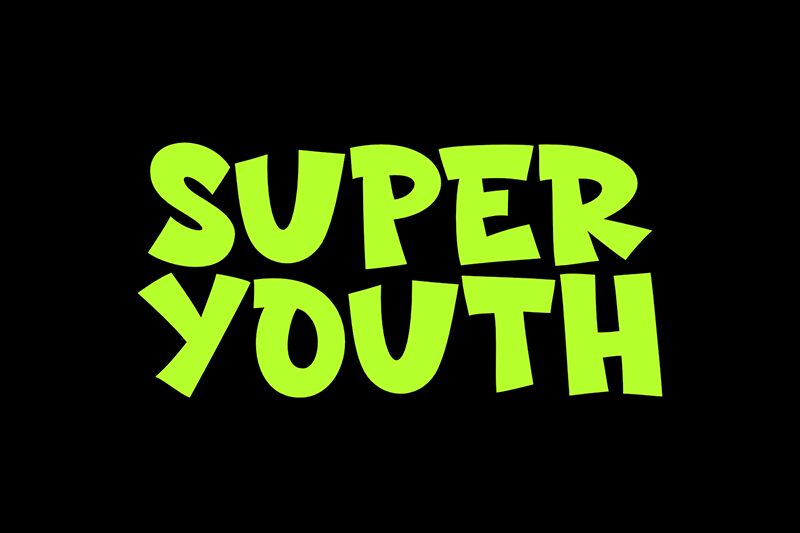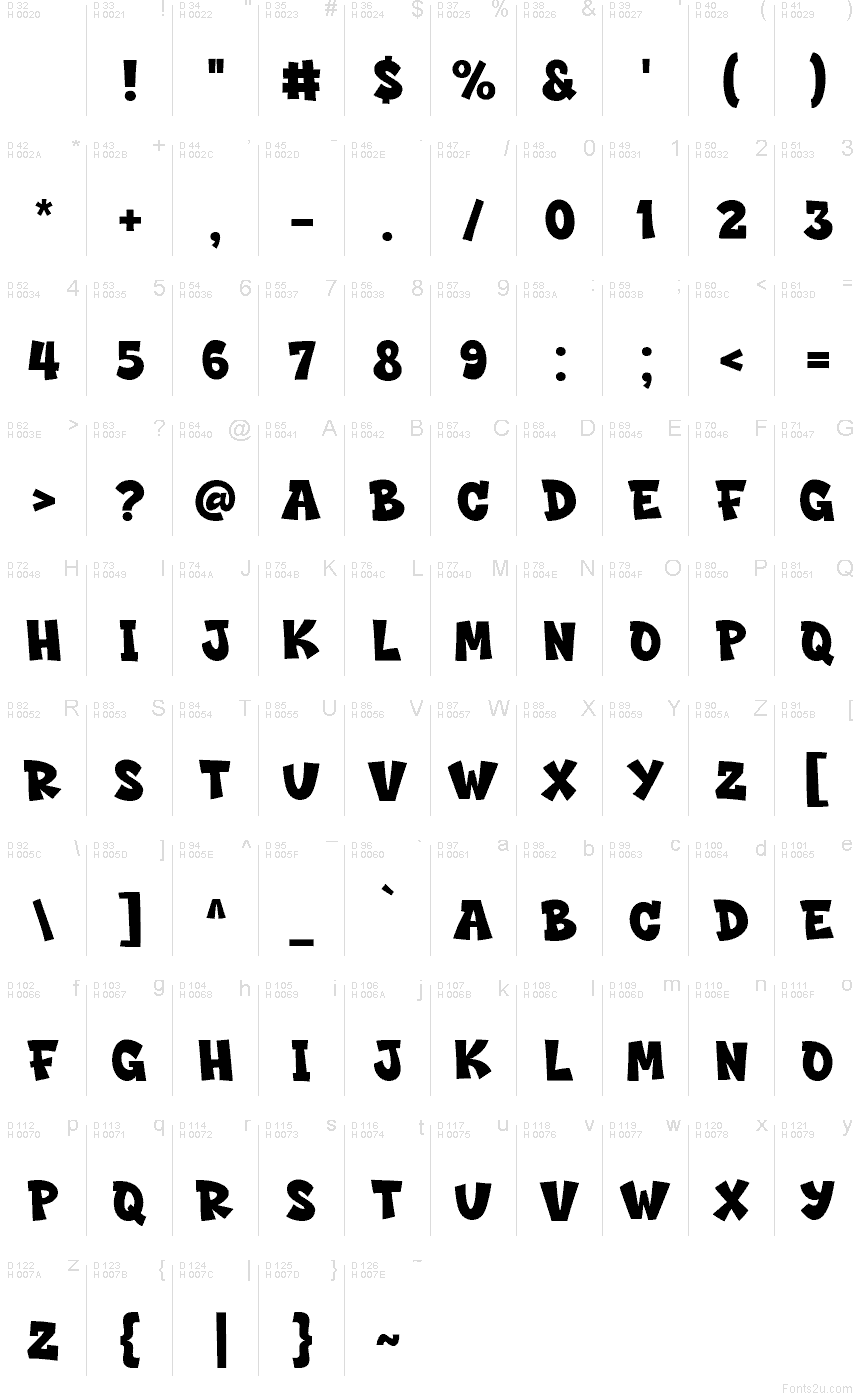
Super Youth Regular
Super Youth ist eine kostenlose Comic-Display-Schrift mit großen, dynamischen Versalien und einem markanten Cartoon-Charakter. Die Buchstaben wirken wie handgeschnitten und leicht uneben, mit geschwollenen Kurven, keilartigen Ecken und einem verspielten Wackeln, das dem gesamten Alphabet einen jugendlichen, plakativen Look verleiht.
Sie eignet sich hervorragend für Kinder-Branding, Party-Flyer, comicartige Überschriften, Snack-Verpackungen und YouTube-Thumbnails, bei denen ein kostenloser Font mit solch einem groben Rhythmus allein durch seine Attitüde überzeugt. Nutzen Sie Super Youth immer dann, wenn die Versalien frech und überdimensional wirken sollen – ideal für Titel oder markante Wörter, die eine mutige, schelmische Silhouette benötigen.